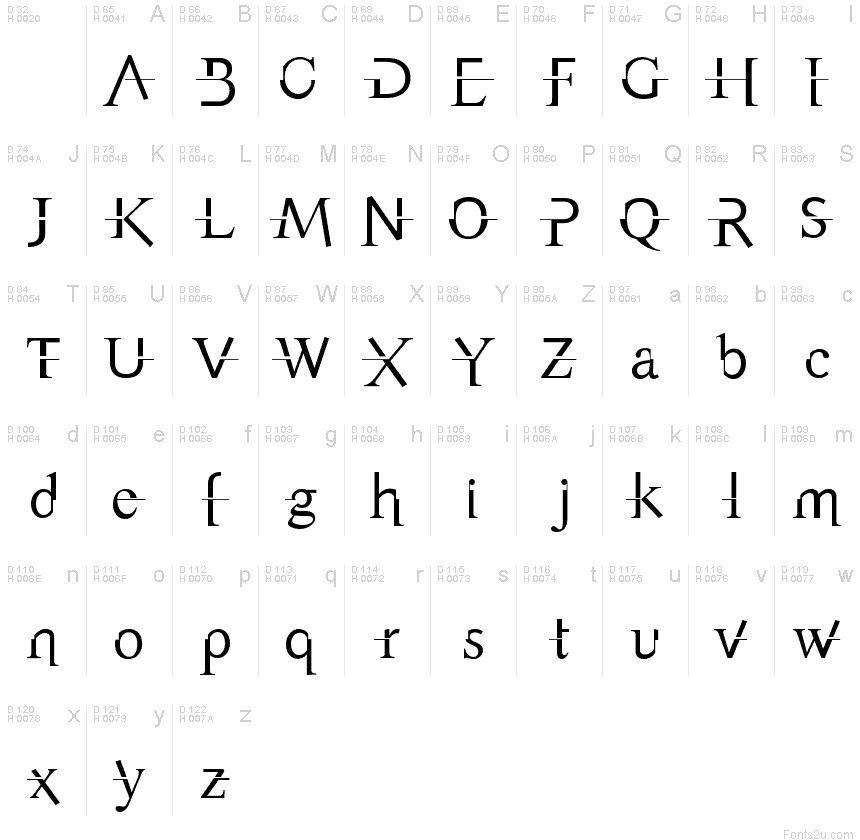
يُعد Appendix خطاً مزخرفاً مجانياً بأسلوب "السيريف"، يجمع بين جرأة شعارات فرق الروك ورقي الخطوط الكلاسيكية القديمة. تتسم ضربات حروفه بالطول والأناقة، حيث تنتهي بزوايا حادة ومنحنيات انسيابية، مما يمنح كل كلمة حضوراً مسرحياً جذاباً يبدو درامياً ومصقولاً في آنٍ واحد. وبفضل تباعد حروفه الضيق وأشكاله الدرامية، يبدو النص وكأنه كُتب يدوياً خصيصاً لملصقات الجولات الفنية أو أغلفة أسطوانات الفينيل الكلاسيكية.
يتألق هذا الخط المجاني Appendix عند استخدامه في أغلفة الألبومات، ومنشورات الحفلات، وشعارات الفرق الموسيقية، وتصاميم المنتجات، والمجلات، والعناوين التحريرية الجريئة التي تحتاج إلى لمسة درامية. تظهر جمالية الحروف بشكل أفضل عند استخدامها بأحجام كبيرة، حيث تبرز دقة الخطوط وانحناءاتها المميزة. ولتحقيق التوازن في التصميم، يُنصح بدمج Appendix مع خط "سان سيريف" هندسي بسيط في النصوص الأساسية أو التفاصيل الثانوية، للحفاظ على تنسيقات لافتة للانتباه مع ضمان سهولة القراءة.